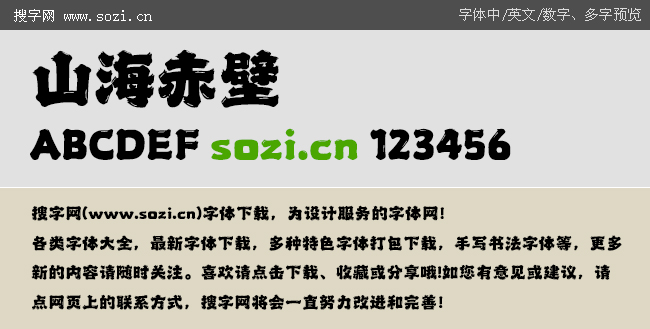
山海赤壁
搜字網(wǎng)提供一款山海赤壁中文字體下載,山海赤壁字體是一款手寫風(fēng)格的毛筆字體。山海赤壁字體粗壯有力,筆畫帶有毛筆的飛白效果,字形端莊大氣,視覺(jué)效果非常不錯(cuò)。適合標(biāo)題設(shè)計(jì)、海報(bào)設(shè)計(jì)、廣告設(shè)計(jì)等應(yīng)用。